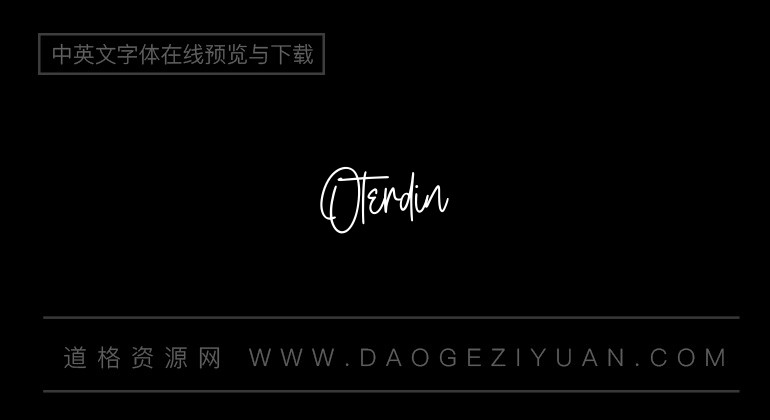
Oterdin
Oterdin 是一款精致的西文字体,由西班牙设计师Juanjo López所设计。它具有细腻的轮廓,柔和的线条,清晰的结构,以及全新的设计理念,为您带来更多的创意和感受。Oterdin字体适合用于商业、广告、网页设计、图形设计、排版等领域。它的多样性和独特的设计风格,能够满足您的各种需求。
Oterdin是一款非常不错的手写艺术字体,具有很好的视觉感,适合于文化类的宣传设计、商业类品牌的广告和产品包装设计以及个性化文字排版等较多场景。